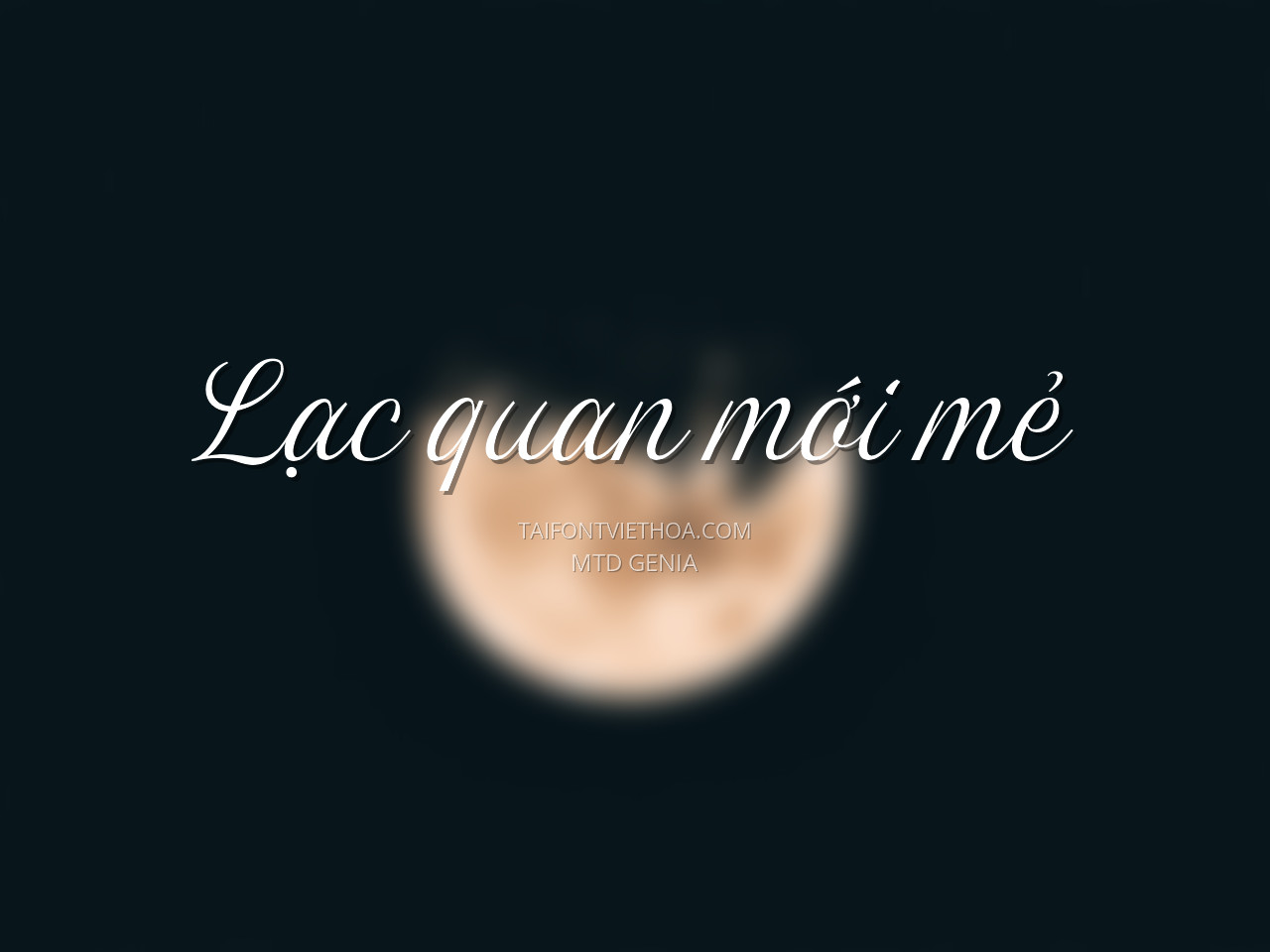
Giới thiệu về font Genia
Genia là một font chữ viết tay thanh mảnh và duyên dáng, được thiết kế bởi Motokiwo Type (MTD). Với kiểu dáng tinh tế mang hơi hướng thư pháp hiện đại, Genia mô phỏng hoàn hảo nét viết tay tự nhiên, mềm mại và đầy cảm xúc. Các nét chữ uyển chuyển, mảnh nhẹ giúp font tạo ra cảm giác sang trọng, nhẹ nhàng và đầy tính nghệ thuật. Phiên bản Việt hóa được thực hiện bởi chính MTD, hỗ trợ đầy đủ tiếng Việt cùng hơn 70 ngôn ngữ khác, đáp ứng tốt các yêu cầu thiết kế đa ngôn ngữ.
Genia đã được taifontviethoa.com chọn lọc và giới thiệu như một trong những font viết tay tiêu biểu, thích hợp với các thiết kế thiên về nữ tính, cá nhân hóa hoặc các ấn phẩm đòi hỏi sự mềm mại và tính biểu cảm cao. Đây là kiểu chữ lý tưởng cho những nhà thiết kế đang tìm kiếm một giải pháp chữ ký hoặc thương hiệu mang phong cách nhẹ nhàng, thanh lịch.
Đặc điểm thiết kế và ứng dụng của font Genia
Font Genia có độ nghiêng nhẹ, đường nét thanh mảnh, uốn cong mượt mà và liên kết tự nhiên giữa các ký tự. Bộ font bao gồm nhiều ligatures và ký tự thay thế (alternates), giúp mở rộng khả năng sáng tạo khi trình bày tiêu đề, chữ ký hay nội dung trang trí. Thiết kế của Genia phù hợp với mọi kích thước hiển thị, đặc biệt hiệu quả trong các thiết kế mang tính nghệ thuật hoặc cá nhân.
Ứng dụng lý tưởng: logo chữ ký, thiệp cưới, tiêu đề blog, bài đăng mạng xã hội, bao bì mỹ phẩm, bìa sách nhẹ nhàng, sản phẩm thủ công hoặc bất kỳ dự án nào muốn thể hiện sự duyên dáng và tinh tế. Ngành nghề phù hợp: thời trang nữ, mỹ phẩm, wedding planner, lifestyle brand, studio ảnh, quà tặng cá nhân, và các thương hiệu hướng đến phong cách nữ tính và sáng tạo.